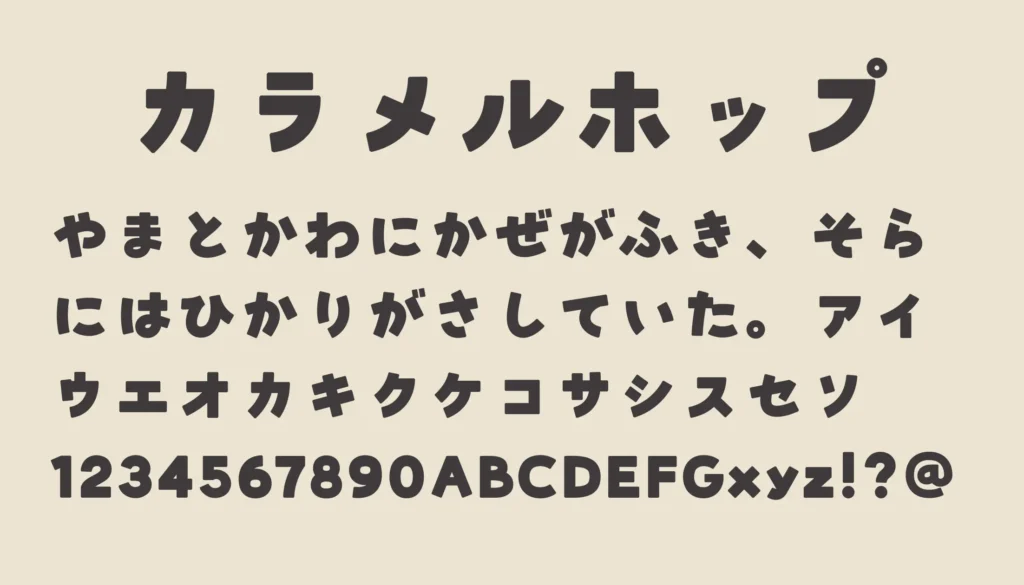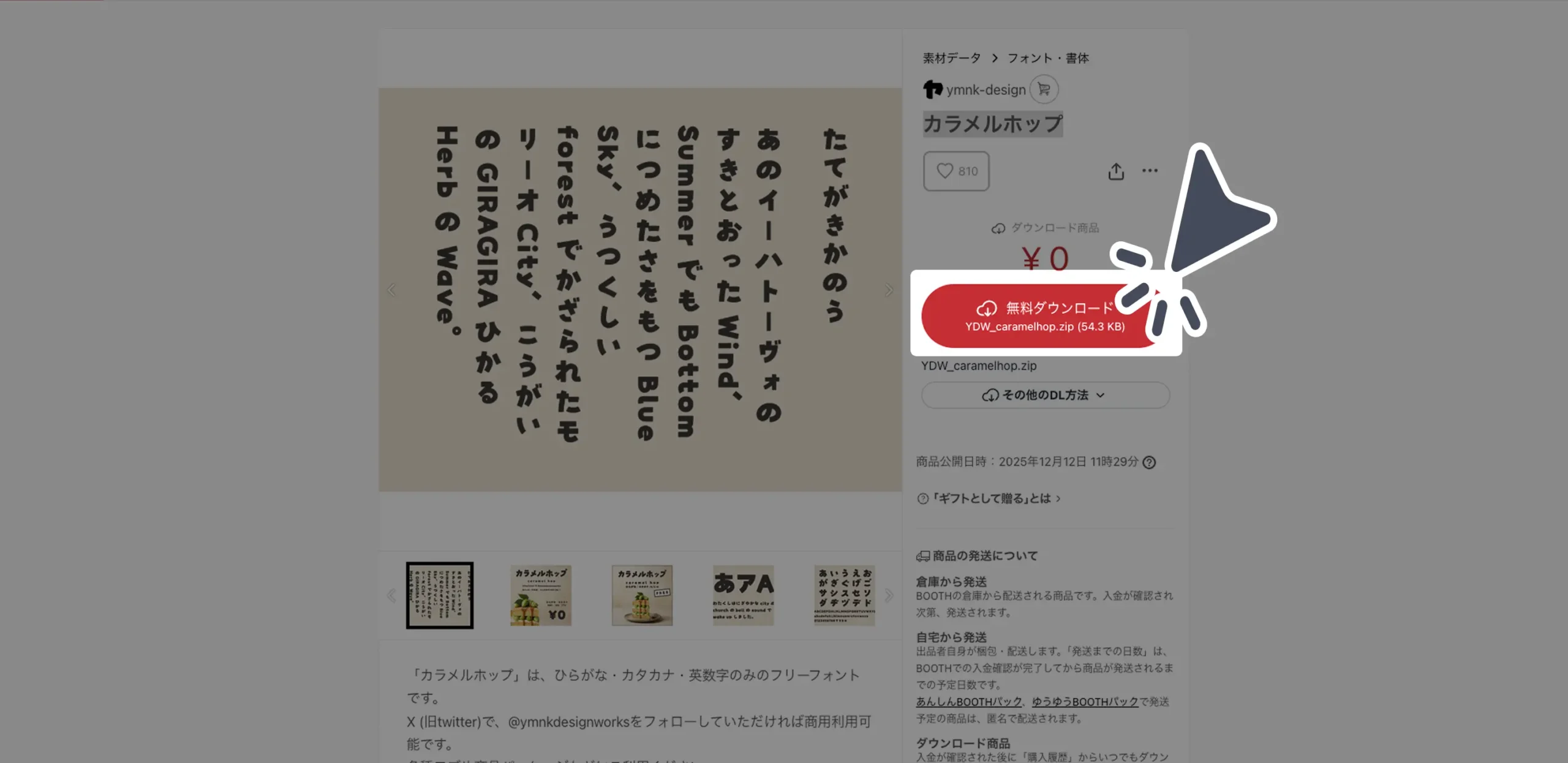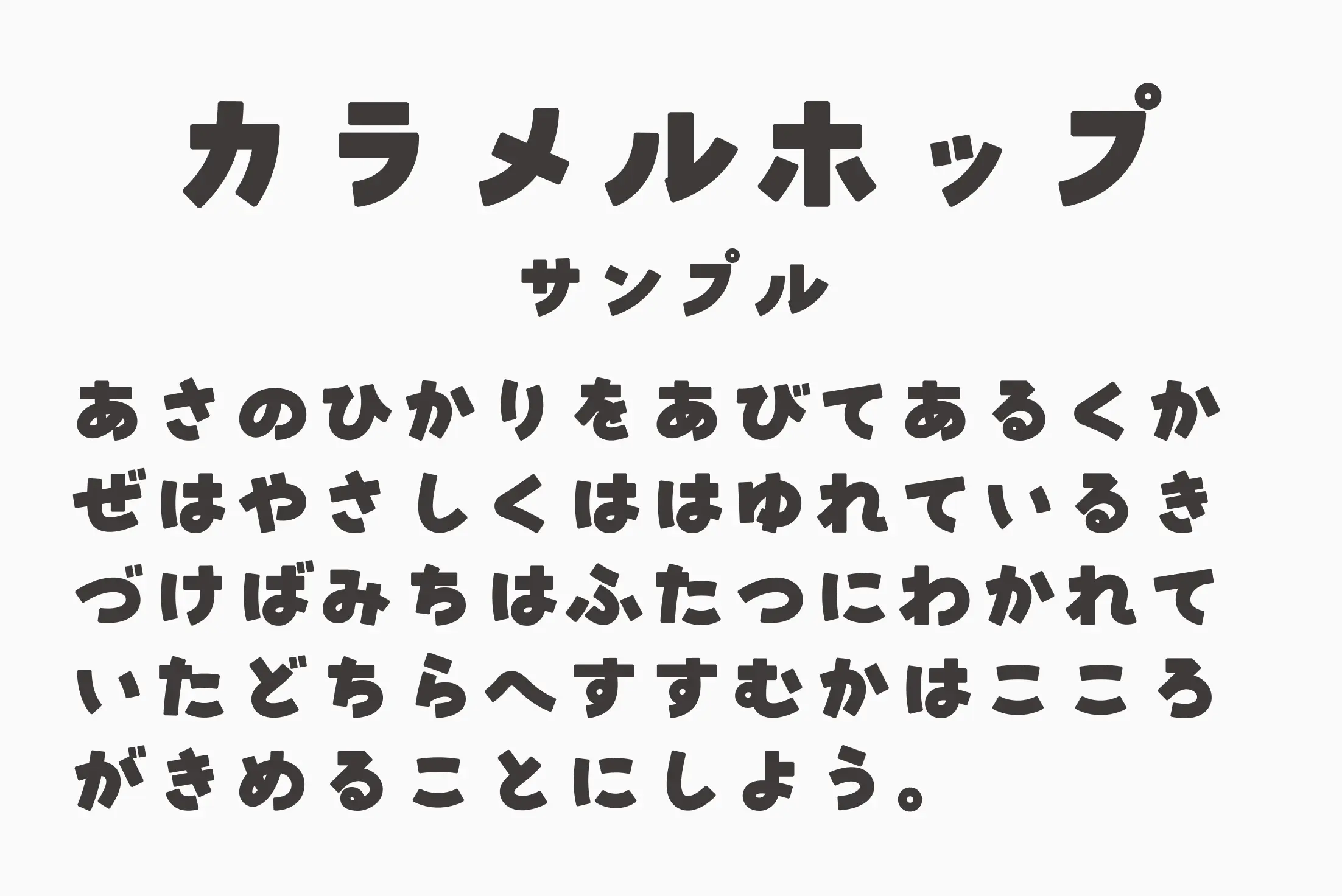
ぷっくり丸みのあるカタカナと、ちょっと跳ねるようなリズム感が特徴のポップ系フォント!レトロ喫茶っぽさもありつつ、今っぽい“ゆるかわデザイン”にもハマる絶妙バランスで、特にパッケージ・サムネ・ショップロゴ系と相性かなり良いです。太めで視認性も高いので、アイキャッチ用途でも使いやすく、「かわいいけど読みやすい」を両立してるタイプ。
カラメルホップ